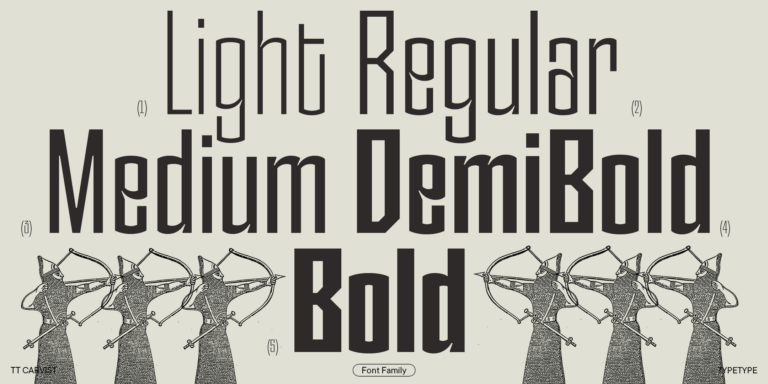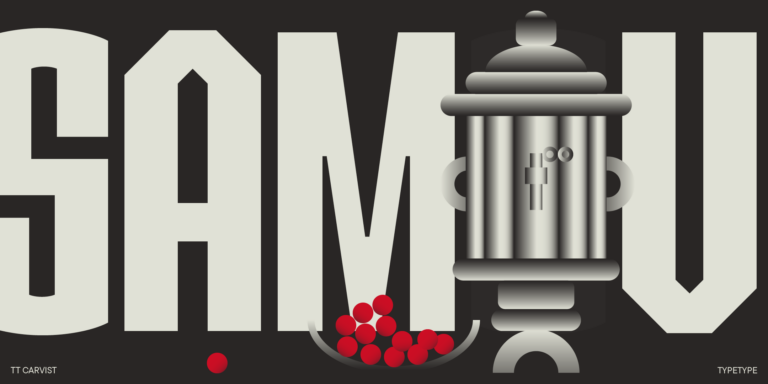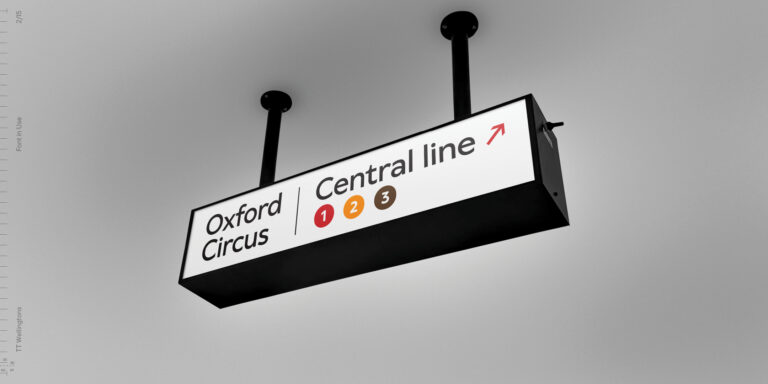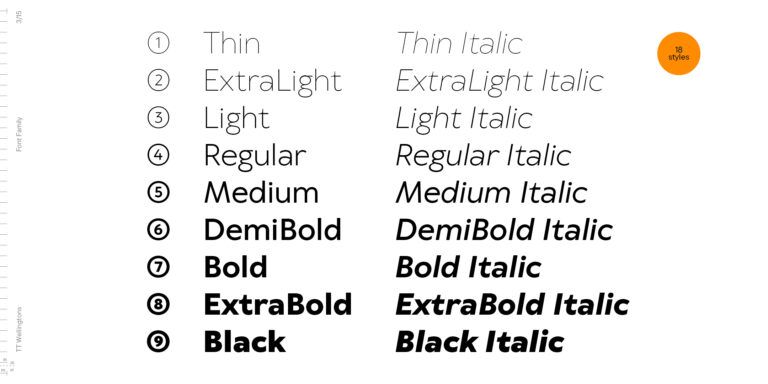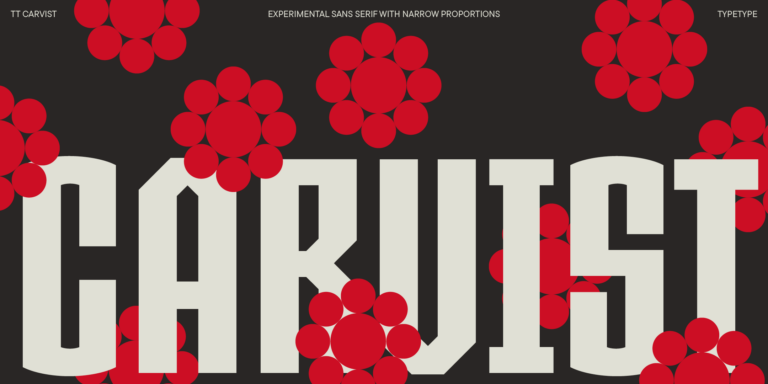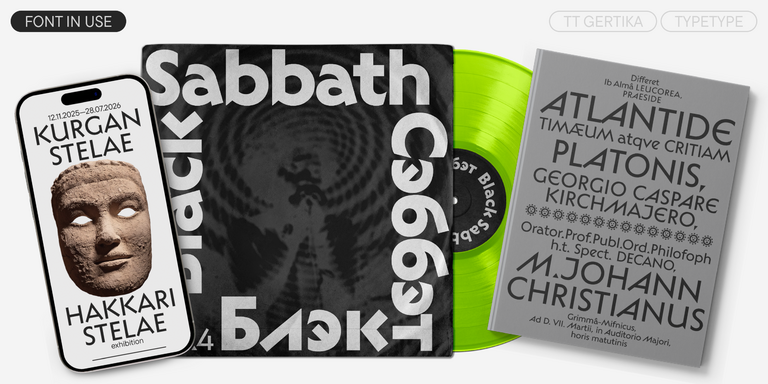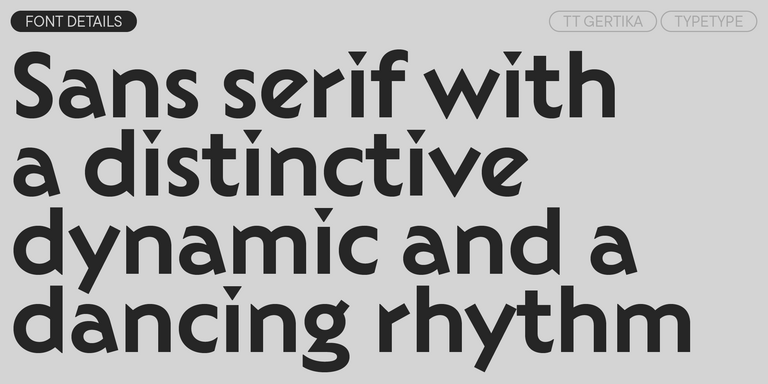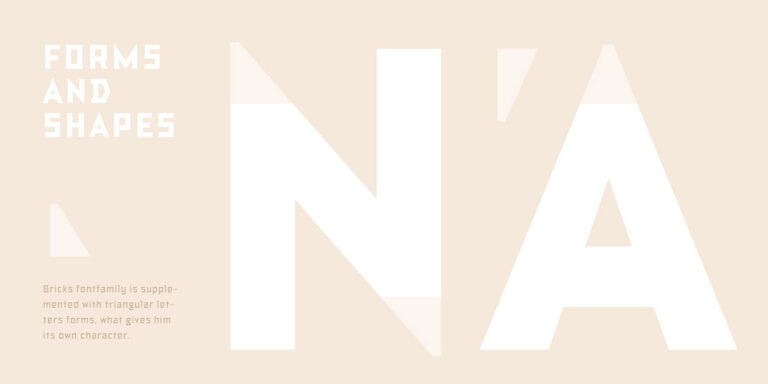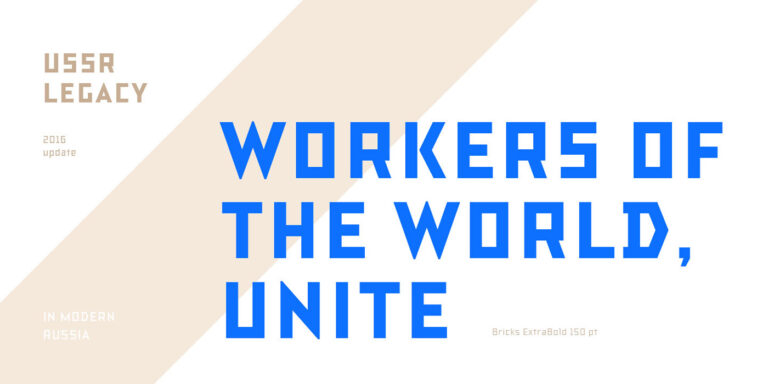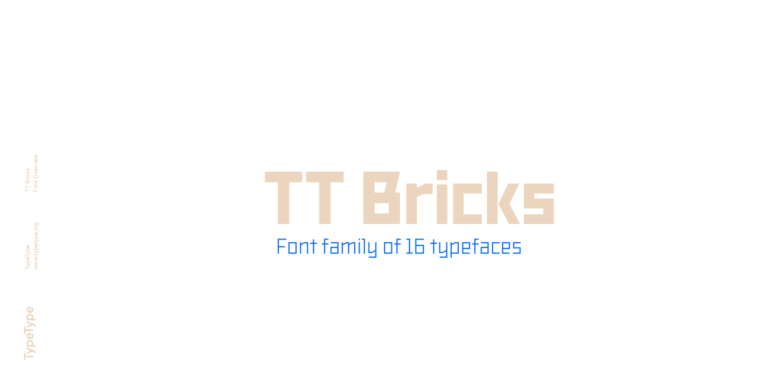
TT Interphases Pro est une sans serif néo-grotesque aux proportions de largeur uniforme.
Polices similaires à Dinamo
Si vous en avez assez des polices surutilisées et que vous recherchez des polices similaires à Dinamo, découvrez nos meilleures alternatives à Dinamo gratuites à essayer, qui présentent des caractéristiques proches ainsi que des éléments de design nouveaux et uniques. Certaines polices appartiennent à la même catégorie typographique, tandis que d’autres conviennent aux mêmes usages ou partagent des traits similaires, tout en se distinguant par leurs détails ou leurs proportions spécifiques.
Trouvez une excellente police de remplacement pour Dinamo et essayez de recréer une ambiance similaire ainsi que l’émotion souhaitée en l’utilisant dans vos designs. Chaque police présentée sur cette page est une alternative à Dinamo, avec une apparence très proche.
TT Gertika est une sans serif géométrique au caractère dynamique et au rythme dansant. L’idée de cette police provient du lettrage figurant sur une affiche américaine de la fin des années 1930.
TT Carvist — atypique, ludique et audacieuse — attire parfaitement l’attention.
TT Wellingtons est une tentative de combiner le style des sans serif humanistes anglaises du début du XXe siècle avec les exigences des grotesques géométriques modernes.
Lors de la création de TT Mussels, nous avons accordé une attention particulière à la composition de grands volumes de texte, et nous pouvons affirmer que TT Mussels appartient à une catégorie rare de polices textuelles technologiques.
TT Bricks est la réponse pour les amateurs de culture soviétique. Nous avons tenté de remonter cent ans en arrière afin de repenser l’ère du constructivisme.